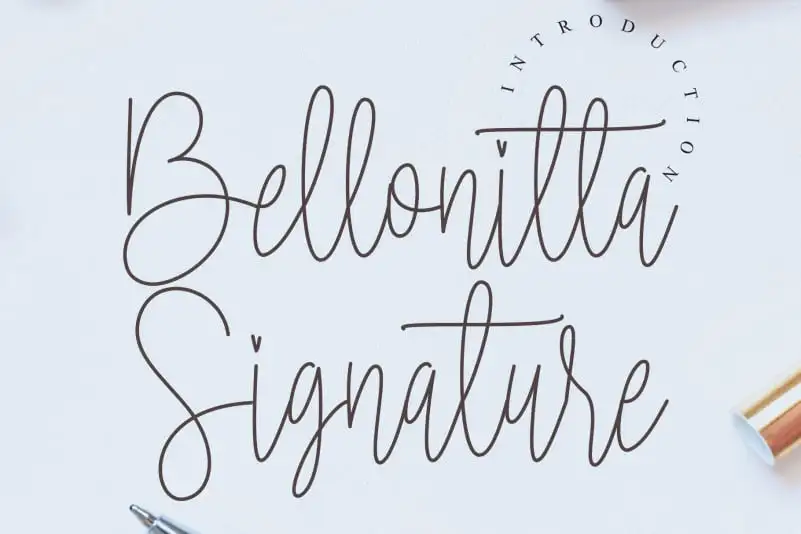
Bellonitta Signature Script Font – Download Grátis
A Bellonitta Signature Script Font é uma fonte de escrita a mão criada pelo Designer CreativeLetter, projetada para oferecer uma experiência única aos amantes do design. Com suas linhas delicadas e traços suaves, essa fonte não apenas recria o estilo elegante da escrita à mão com precisão e detalhes meticulosos, mas também eleva-a a um nível superior de sofisticação e exclusividade. Perfeita para os projetos que exigem um toque personalizado e profissional, esta fonte é uma escolha perfeita para designers gráficos em busca de adicionar um elemento único a seus trabalhos. Suas variações sutis dão ao texto um contraste interessante sem perder o seu estilo fluido, tornando-a ideal tanto para textos grandes quanto menores. Com sua natureza elaborada e detalhada, a Bellonitta Signature Script Font se destaca como uma opção exclusiva e versátil. Ela é perfeita para marcar seus projetos de forma única e imprimi-los com um toque personalizado, garantindo que qualquer projeto seja notado por sua elegância e originalidade.